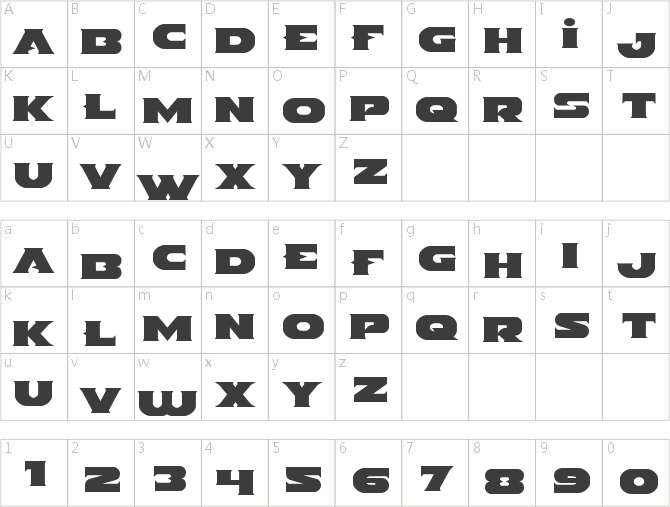
字體名稱: indigod
indigodemonexpand
indigodemonexpand介紹
indigodemonexpand字體字庫是一款讓人賞心悅目、百看不厭的英文字體,適合各類廣告和產(chǎn)品包裝設計應用,字體大小0.04MB,格式為ttf字體,上傳用戶是23KUN,作者/版權(quán)方為未知